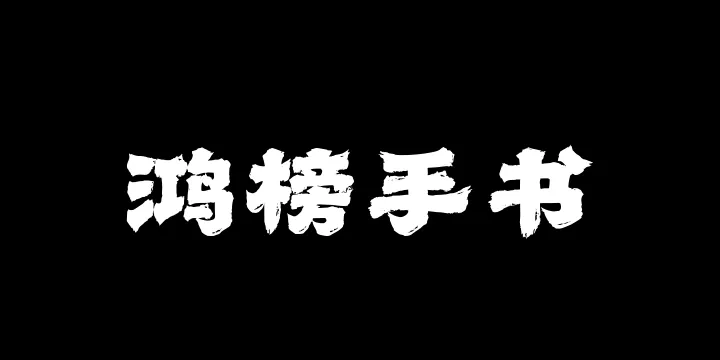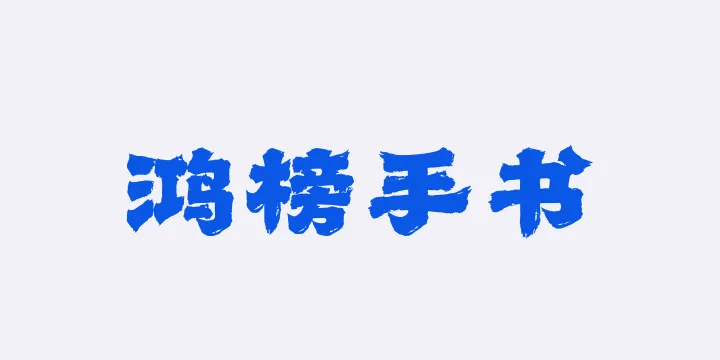
字体全名: 山海鸿榜手书W
字体简介: 山海鸿榜手书,是一款全新的毛笔风字体,包含汉字9169个,符号200+个。该字体的毛笔笔锋狂野有力,,非常醒目!字形古朴浑厚,在浑厚的同时而又极富张力。它的笔画充满力量感的同时,用蕴含着朴拙感。在粗细的纵横间,拥有非常规的张力特性。笔画的飞白效果使字体的气息更加流畅,笔画间的关系密不可分,同时也增加了字体的自由洒脱之感。